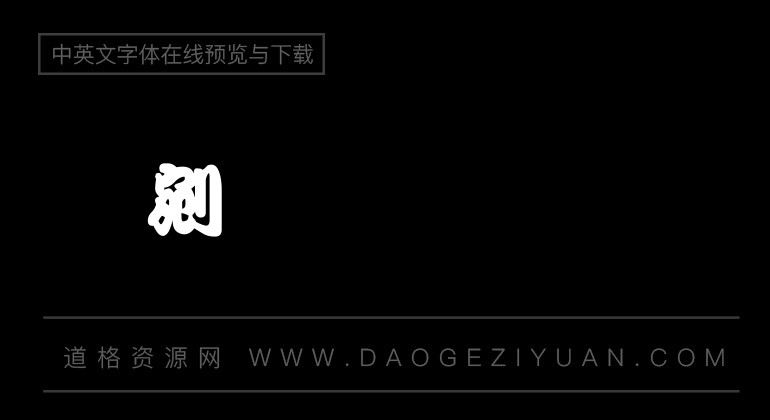
? 勘亭流书法是宋代书法家勘亭的书法流派,他的书法特点是把篆书、隶书、楷书三种书体结合在一起,经过一定的演变形成了一种新的书体。勘亭流书法以勘亭的《书圣语录》为主,以勘亭的书体为基础,以篆书、隶书、楷书三种书体为基本元素,具有楷书的端庄、篆书的细腻、隶书的活泼的特点,墨色浓郁,笔画细腻,结构严谨,笔势舒展,有“书中有画”的效果。文件名:ShuFaJiaKanTingLiu-1.ttf
书法家勘亭流是一款非常不错的手写艺术字体,具有很好的视觉感,适合于文化类的宣传设计、商业类品牌的广告和产品包装设计以及个性化文字排版等较多场景。